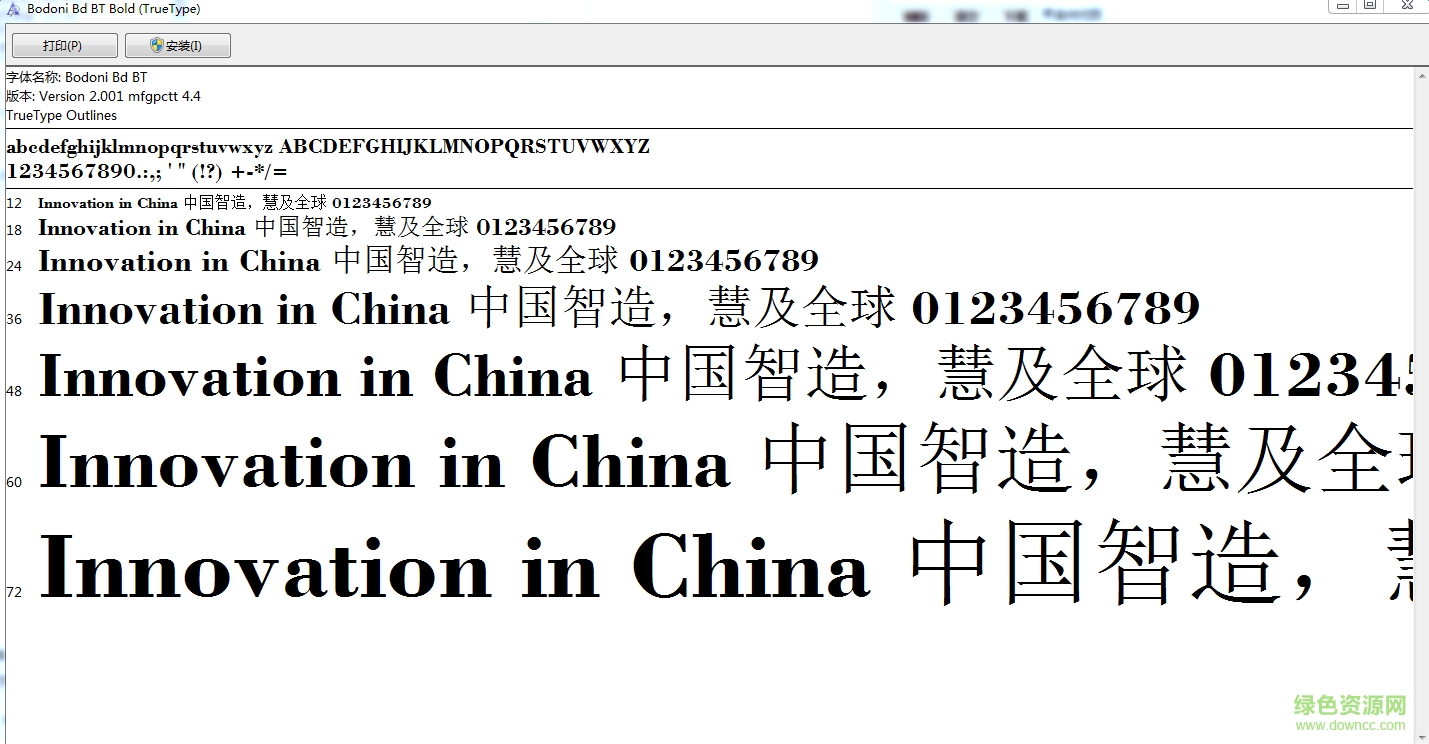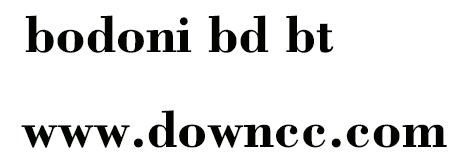
bodoni bd bt bold字體是一款視覺效果強(qiáng)烈的英文字體,字體結(jié)體飽滿,粗細(xì)變化得宜,大氣醒目,可使用的領(lǐng)域極其廣泛,歡迎大家免費(fèi)下載!
Bodoni以出版印刷之王 Giambattista Bodoni的名字命名,他是一位多產(chǎn)的字體設(shè)計(jì)師,也是一個(gè)偉大的雕刻師。他設(shè)計(jì)的字體被譽(yù)為現(xiàn)代主義風(fēng)格最完美的體現(xiàn)?,F(xiàn)代字體代表了十八世紀(jì)晚期十九早期的字體設(shè)計(jì)發(fā)展一種總結(jié),其他類似的如法國的Didot(1689-1853)字系和德國的J. E. Walbaum都反映了“現(xiàn)代風(fēng)格”的不同面貌。